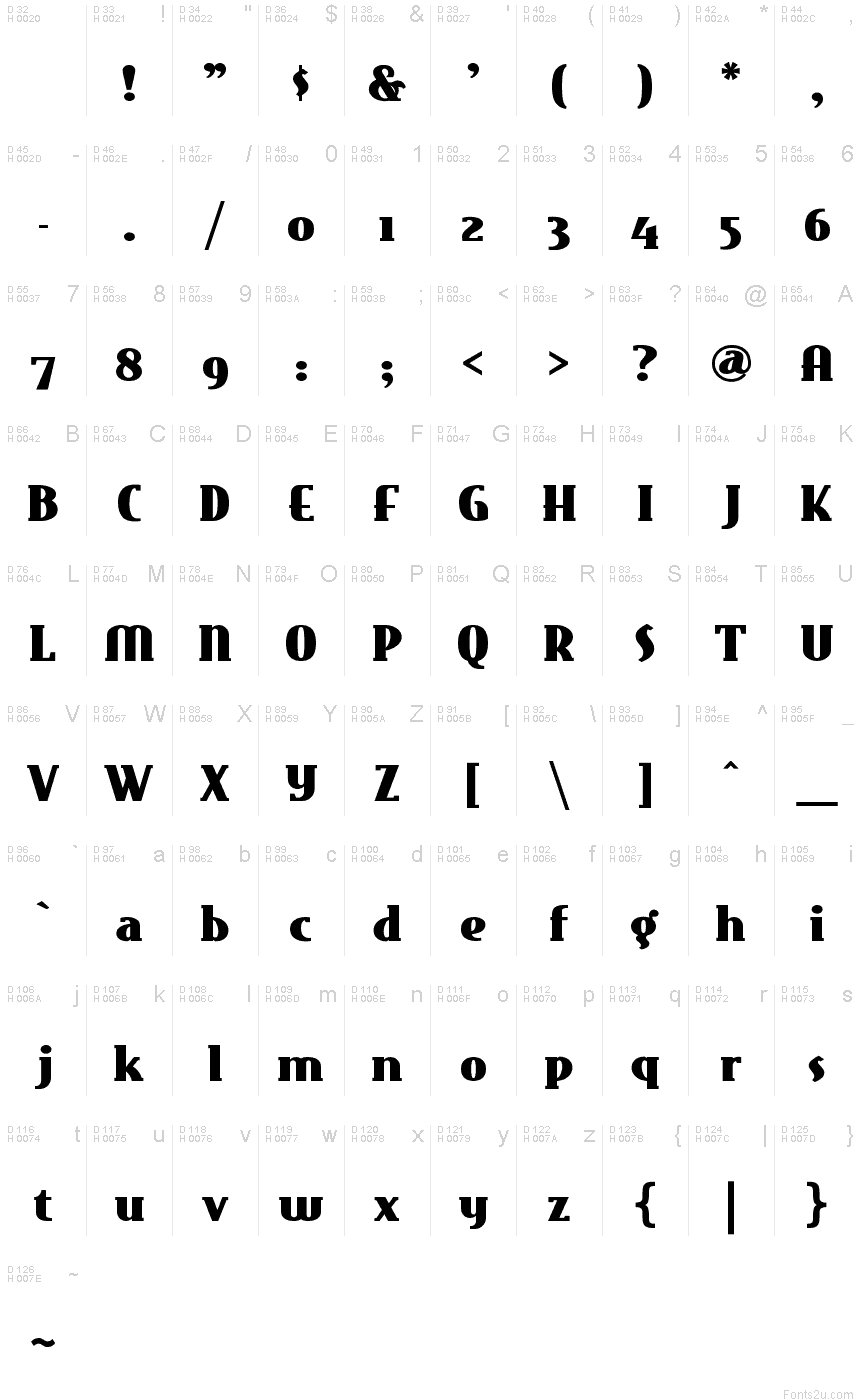
EastMarket od Nicka Curtisa to darmowy, dekoracyjny krój szeryfowy, który łączy w sobie ciężar dawnych szyldów rynkowych z charakterem nagłówków gazet w stylu vintage. Grube, blokowe pociągnięcia spotykają się tu z zaokrąglonymi łukami i masywnymi szeryfami, dzięki czemu każde słowo sprawia wrażenie nadrukowanego, solidnego i lekko teatralnego. Ciasny rytm i odważne sylwetki liter nadają krojowi dotykową, nasyconą atramentem obecność, która przyciąga wzrok z drugiego końca pomieszczenia.
Ten darmowy font świetnie sprawdza się w identyfikacji wizualnej targowisk, opakowaniach w stylu retro, tytułach plakatów, menu, szyldach sklepowych i wyrazistych logotypach. Użycie EastMarket w dużych rozmiarach pozwala wybrzmieć szerokim krzywiznom i gęstym formom liter. Połącz go z czystym krojem bezszeryfowym typu grotesque w mniejszych tekstach, a uzyskasz mocną, nostalgiczną hierarchię, która zachowuje czytelność w nowoczesnych projektach.